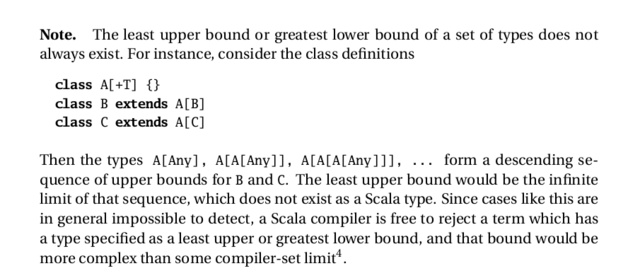
Gute Code-Schrift/Brotschriftt-Kombinationen für Programmierbuch?
ich frage mich zur Zeit gerade, ob ihr ein paar Kombinationen empfehlen könnt, bei denen die Brotschrift zur “Code”-Schrift passt, so dass die Code-Schrift nicht nur in Beispielen sondern auch “inline” im Text eingesetzt werden kann.
Bisher habe ich lediglich die Utopia/LuxiMono-Kombination gefunden, die mir recht gut gefällt:
Im Allgemeinen habe ich den Eindruck, dass es viele Mono-Schriften gibt, die am Bildschirm sehr gut funktionieren, aber im Print (oder auch nur als PDF) unbrauchbar sind. Kann das jemand bestätigen?
Bei größeren Schriftsippen gibt es ab und zu auch eine „Mono“-Familie. Abgesehen davon, dass sie gedruckt nicht besonders gut aussehen, ist das auch bei den kostenlosen DejaVu-Schriften so.
Wie Cajon schon angedeutet, stößt man da bei den großen, besser ausgebauten Schriftsippen meist auf ganz brauchbare Ergebnisse. Spontan fallen mir folgende, qualitativ recht hochwertige Kombinationen ein:
· FF Quadraat Sans/Quadraat und FF Quadraat Sans Mono
· LF TheSans/TheSerif und LF TheSansMono
· Fedra Sans/Serif und Fedra Mono
· FF Fago/Fago Correspondence Serif und FF Fago Mono
· PTL Manual Sans/Slab und PTL Manual Mono
Hier noch ein paar Beispiele von schönen, noch nicht ganz so »abgegriffenen« Grotesk-Varianten, welche man sich aber unter dem Aspekt »Mengensatz-Tauglichkeit« vorher noch mal genauer ansehen sollte:
· FF Nuvo und FF Nuvo Mono
· PTL Notes und PTL Notes Mono
· Typonine Sans und Typonine Sans Mono
· Simplon BP und Simplon BP Mono
Und selbst die »klassische« Univers bekommt man in der Next-Version mittlerweile mit Mono-Schnitten.
Im Allgemeinen habe ich den Eindruck, dass es viele Mono-Schriften gibt, die am Bildschirm sehr gut funktionieren, aber im Print (oder auch nur als PDF) unbrauchbar sind. Kann das jemand bestätigen?
Was meinst Du für Schriften? Nenne doch mal ein paar Beispiele.
Ich finde, viele der bekannten dicktengleichen Schriften machen auch im Druck eine gute Figur (natürlich von den ganzen Bildschirm-Rasterschriften abgesehen), etwa Monaco, Andale Mono, Lucida Typewriter, Consolas oder Inconsolata.
Ein paar Mischungsvorschläge:
Letter Gothic Text + Letter Gothic + Meta Serif
Hellschreiber Sans + Hellschreiber Serif + Courier
Lucida in verschiedenen Schnitten
Akkurat + Akkurat Mono (+ eine Antiqua)
Nimbus Sans + Nimbus Sans Mono (+ eine Antiqua)
Da ich berufsbedingt oft mit EDV-Büchern konfrontiert werde, würde ich bei der Auswahl der Schriftart darauf achten, dass die Ziffer 0 und das große „O“ sowie die Ziffer 1, das kleine „l“ und das Pipe-Zeichen „|“ gut zu unterscheiden sind.
Auch können verschiedene Zeichenkombinationen für Kommentare wie //, /*, <!-- vorkommen, die sich sauber ins Schriftbild integrieren sollten, ohne zu kollidieren.
Da die diversen Sonderzeichen wie #, %, @ und $ oft zur Kennzeichnung von verschiedenen Sprachkonstrukten verwendet werden, müssen sie so gestaltet sein, dass sie nicht wie Fremdkörper wirken (so finde ich den Ausdruck „@a“ z.B. in der Nuvo Mono ziemlich angefressen).
Persönlich verwende ich als Schriftart für meine Terminals und für meinen Texteditor die Inconsolata oder die Andale Mono. Ob diese Schriften die Anforderungen an ein gedrucktes Dokument erfüllen, vermag ich nicht zu sagen.
Danke erst einmal an alle Antworten! Ich realisiere jetzt, dass mein Screenshot viel zu klein war, um aussagekräftig zu sein.
Das Problem, auf das ich gestoßen bin, ist dass sich zu vielen Brotschriften keine Schrift mit fester Breite finden kann, die nicht wie ein Fremdkörper aussieht (wie von Jmk angesprochen).
Meines Erachtens liegt das daran, dass die meisten Mono-Schriften serifenlos sind und deswegen sich schlecht ins Schrifbild einfügen lassen.
Eine Möglichkeit wäre natürlich die Nutzung von Schriftfamilien wie die DejaVu Serif + DejaVu Mono (wie Cajon angemerkt hat), aber da ist selbst die DejaVu Serif (als “Slab-Serif”) nicht wirklich für den Mengensatz geeignet.
Viele der restlichen Vorschläge, also vernünftige Antiqua + Serifen-Mono (danke R::bert, Joshua), kranken meiner Meinung nach zum Großteil am geringen Kontrast der Monoschrift.
Echt schwierig, eine gute Lösung zu finden. Fällt jemand noch eine kontrastreiche Monoschrift mit Serifen ein?
Ich glaube auch, er meint den Kontrast zwischen Haupttext-Antiqua und Dicktengleicher. Mir wäre wichtig, daß die beiden Schriften gut zu unterscheiden sind, damit auch im Haupttext stehende Code-Ausdrücke (z. B. einzelnen Befehlsnamen o. ä.) sofort als solche erkannt werden.